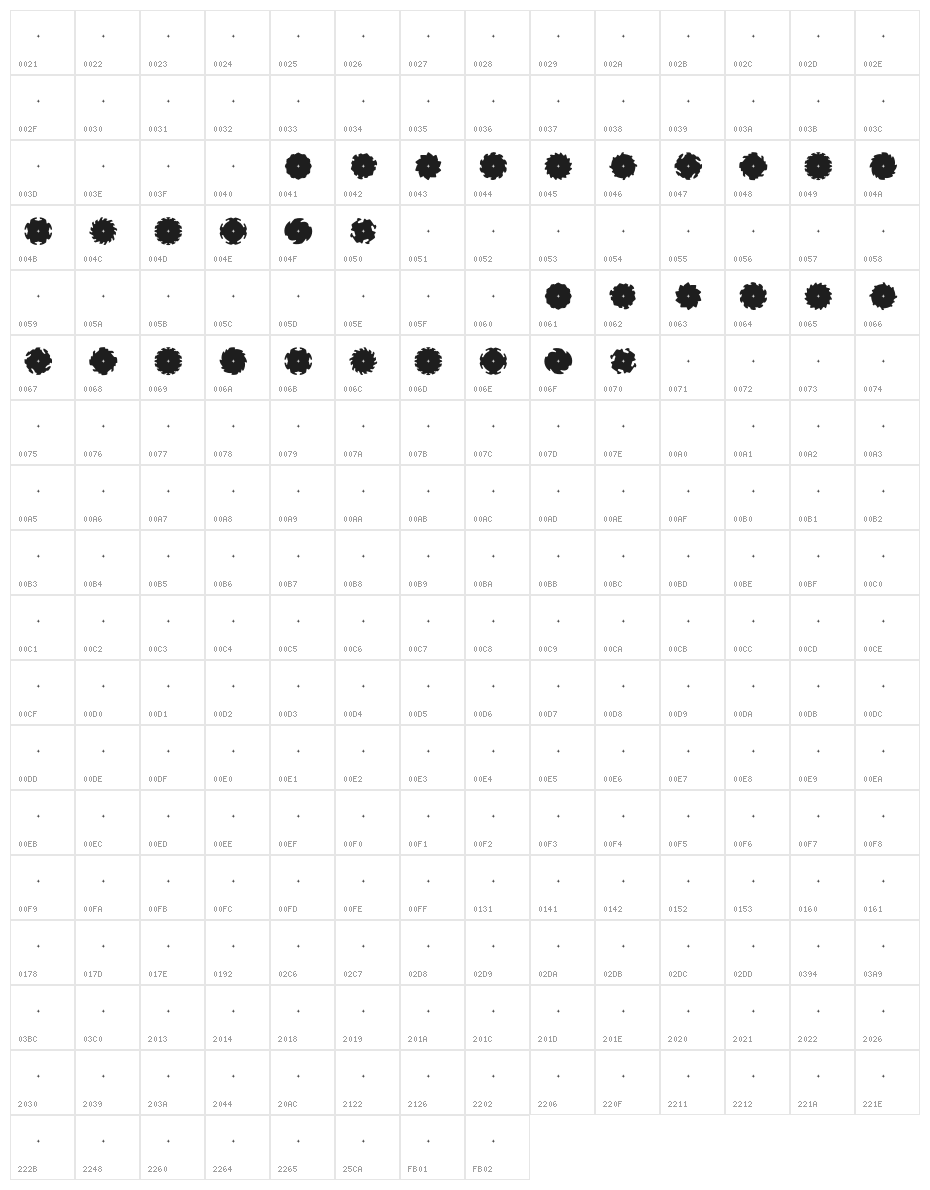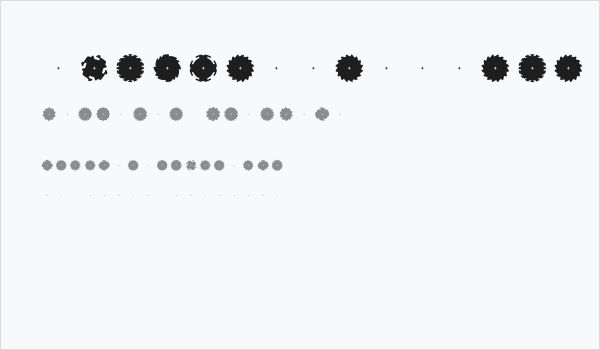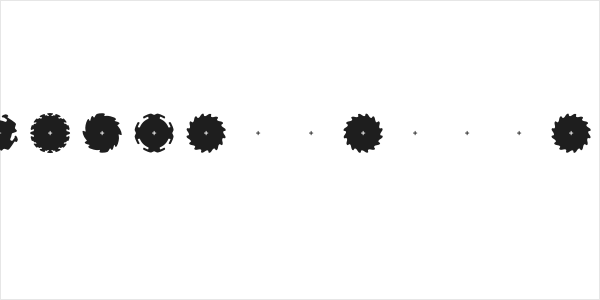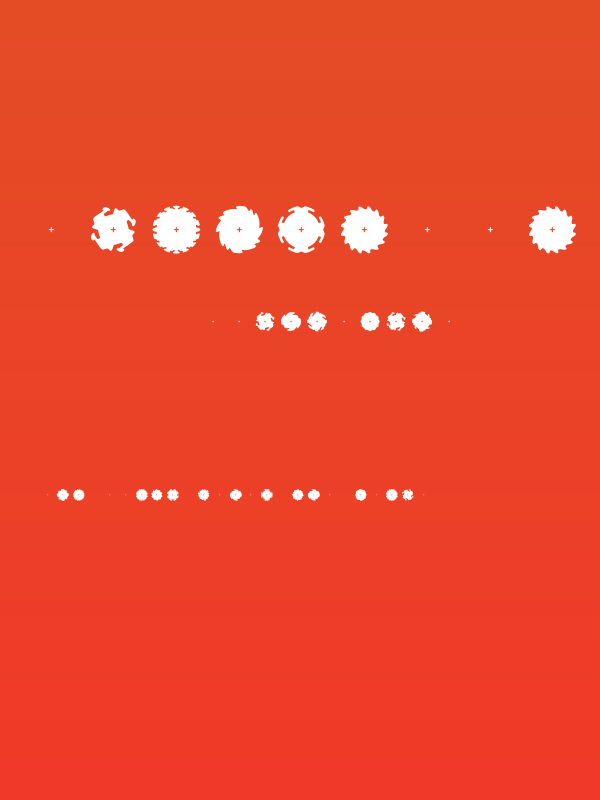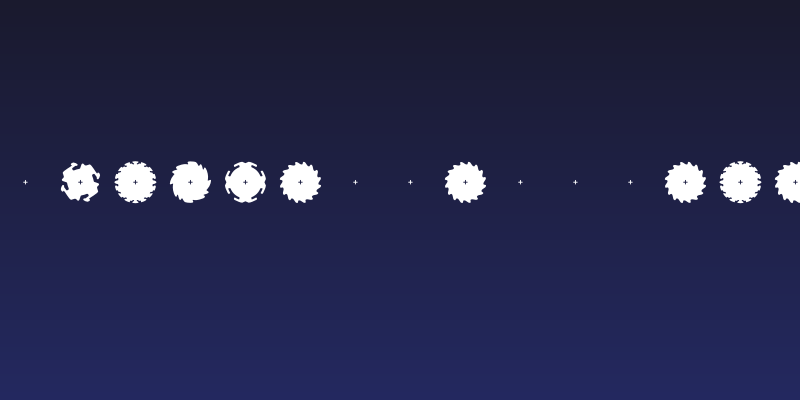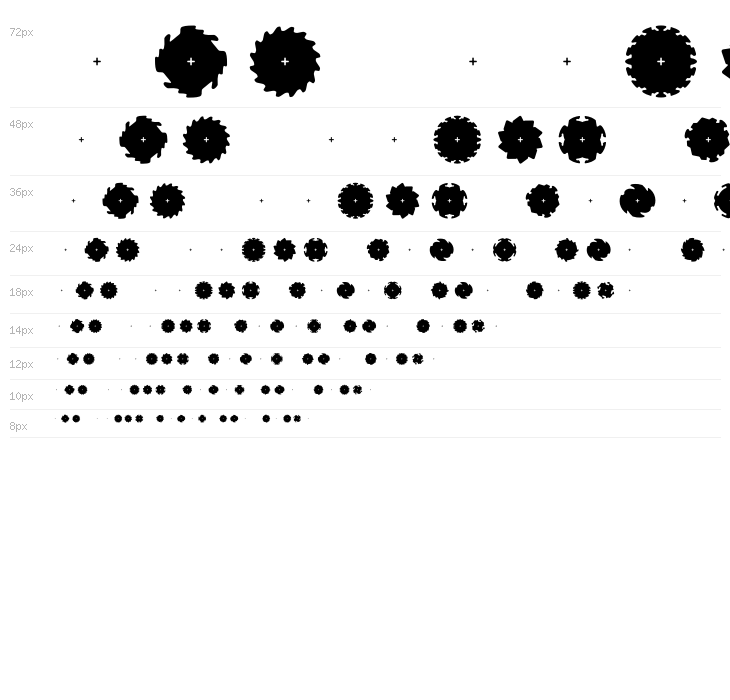
Spijner-Extreme Font
✎ Thick
| 整体风格 | Industrial, Edgy, Mechanical |
| 使用场景 | Logos, Posters, Thematic Designs |
| 推荐项目 | Ideal for industrial-themed posters, album covers, or branding that requires a bold, mechanical look. |